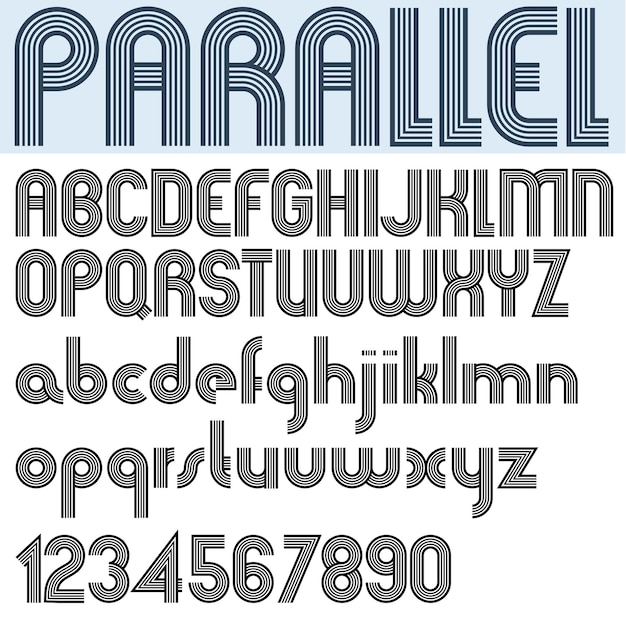
Czcionka w stylu „PARALLEL” w paski w stylu retro, wersja lekka, alfabet wektorowy, modny i stylowy wzór liter. Najlepsze do wykorzystania w plakatach i projektach graficznych w stylu retro. Wektor.